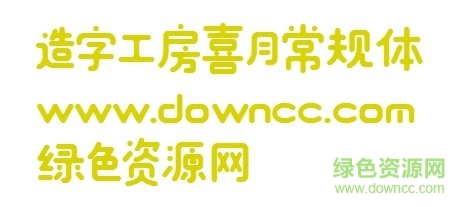
造字工房喜月體有著大方清爽的設(shè)計,無多余的點綴,是一款有個性姿態(tài)的黑體字體,給人眼目一新的柔和體驗,中文字正腔圓英文圓潤簡潔,藝術(shù)效果不錯,快來綠色資源網(wǎng)試試吧!
造字工房喜月體,其字形大小不一、參差錯落,造型或倚或正,或重或輕,筆畫恣意灑脫、率真拙樸,隨性又不拘謹(jǐn),妙趣橫生。此款字體適用于書籍、報刊雜志標(biāo)題、電視字幕、廣告設(shè)計等視覺環(huán)境,有著極強的應(yīng)用空間。